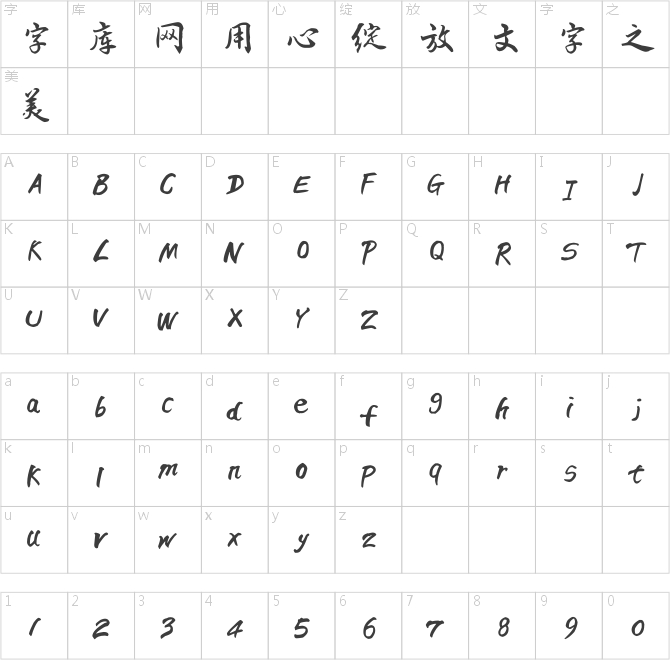
漢呈王天喜江湖體 詳情頁
字體名稱: 漢呈王天喜江湖
漢呈王天喜江湖體
漢呈王天喜江湖體介紹
漢呈王天喜江湖體字體字庫是一款讓人賞心悅目、百看不厭的中文字體,適合各類廣告和產(chǎn)品包裝設(shè)計應(yīng)用,字體大小2.95MB,格式為ttf字體,上傳用戶是漢呈字庫,作者/版權(quán)方為漢呈字庫